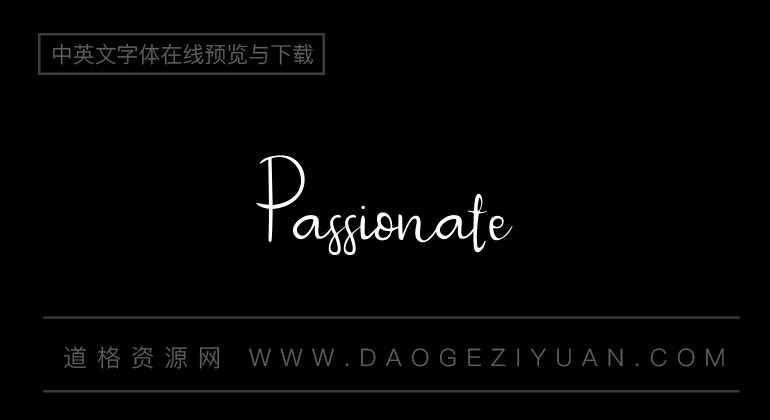
Passionate 是一种优美的手写风格字体,它的字母有强烈的笔画和流畅的曲线,给人一种充满活力和热情的感觉。这种字体的特点是具有良好的可读性,同时还具有非常美观的视觉效果。Passionate 字体非常适合用于设计卡片、海报、标志、标题、宣传册等需要突出标题或者重点信息的场合。此外,它还支持多种语言,可以满足全球不同地区和文化的需要。内容介绍
Passionate是一款非常不错的手写艺术字体,具有很好的视觉感,适合于文化类的宣传设计、商业类品牌的广告和产品包装设计以及个性化文字排版等较多场景。